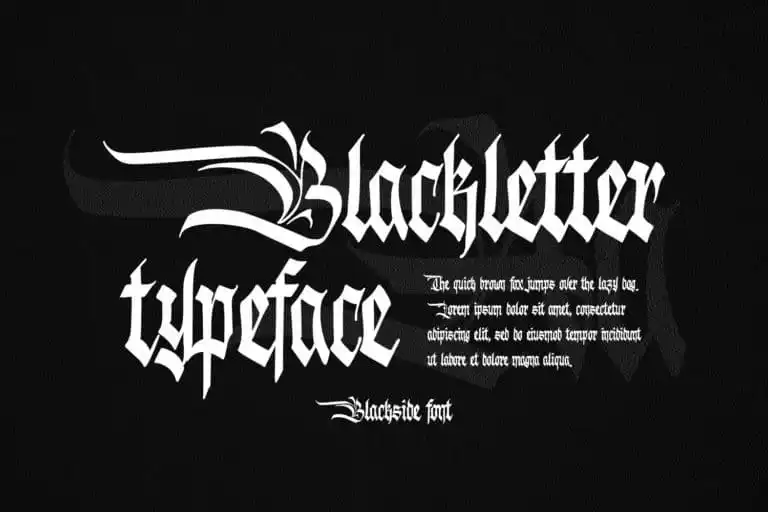
Blackside Blackletter Font – Download Grátis
A Blackside Blackletter é uma fonte inspirada nas antigas postagens de propaganda, criada sob medida para incorporar a sensação natural do trabalho manual no seu identidade visual. Esse é um verdadeiro ‘blackletter’ que transmite uma sensação autêntica e poderosa. O design da Din Studio concebeu a fonte com cuidado para que ela seja ideal para projetos de marca, como logomarcas ou impressão em camisetas, além de muito mais. Com sua bold e imediata aparência, esta font está repleta de aplicabilidade em diversos contextos. Não apenas é uma excelente escolha para qualquer projeto de branding, mas também tem um poder que se estende ao seu uso em diferentes ambientes. Seja ela a cara de sua próxima camiseta customizada ou o coração do seu próximo logotipo, esta fonte Blackside Blackletter oferece tanto força quanto graça.